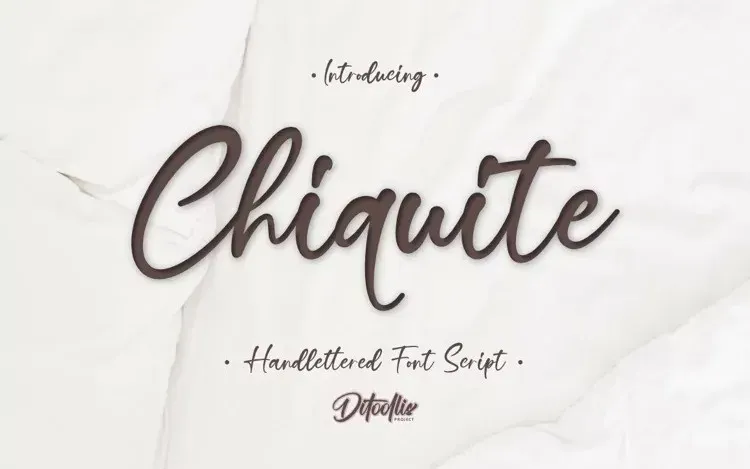
A ‘Chiquite Font’ é uma nova tipografia casual moderna criada pelo Ditoollis Project para quem busca uma paleta de letras elegante e dinâmica. Essencialmente, essa fonte transmite feminismo e humanismo, facilitando a composição de textos com harmonia. Ela combina bem em diferentes contextos, desde cartões de visita até cartazes e revistas de quadrinhos. Perfeita para criar identidades visuais modernas e sofisticadas para marcas, logotipos ou até mesmo convites. Com seu design fluido e fácil de usar, a ‘Chiquite Font’ é uma escolha perfeita para quem busca um toque sofisticado em seus projetos.